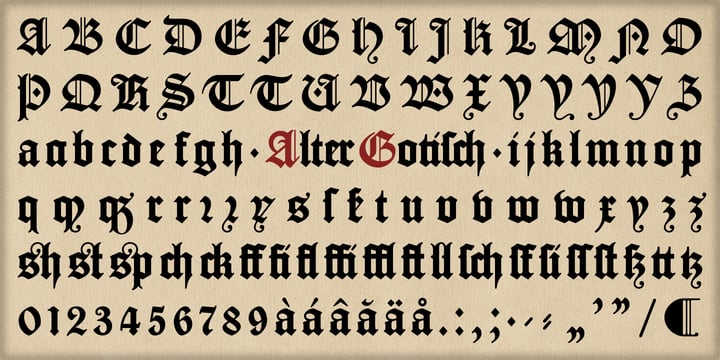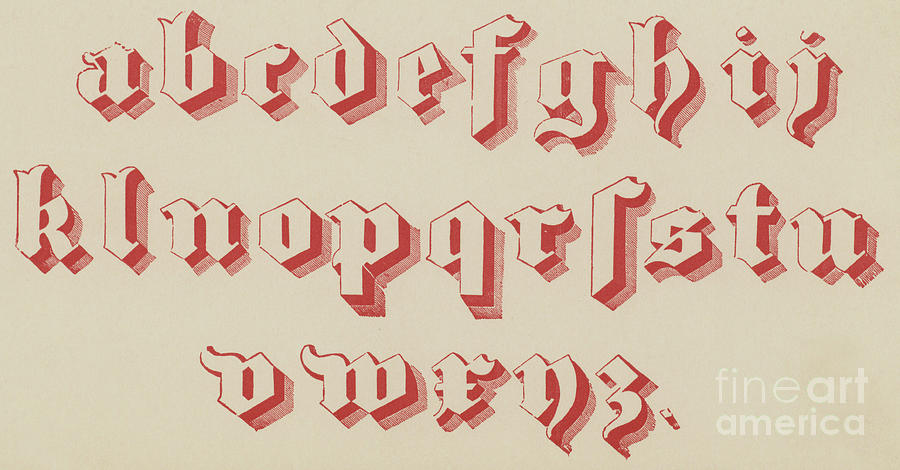
Как шрифты питают культурные войны
Типографика может представлять собой не только визуальные эффекты речи, но и серьезную опасность для общества.
Сегодня типографика словно возрождается из пепла. Обычно она старается быть невидимой, но в последнее время стала знаком изысканности для людей.
Внезапно, люди, далекие от профессии дизайнера, стали задумываться о мелочах. В том числе и о типографике продукта, с которым они взаимодействуют. В этом году премия Oscar обзавелась визуальной иерархией на карточках представления лауреатов, читатели популярного комикса XKCD никогда не упустят возможности указать на плохой кернинг, а в интернете кто-то постоянно шутит над шрифтом Comic Sans.
Но, сосредотачиваясь на мелких недостатках, мы упускаем общий смысл. Типографика не просто служит улучшению читабельности визуальных эффектов. Типографике свойственно скрытое влияние: она может обозначить опасные идеи, облагородить тиранию и разорвать связи между братскими народами. В некоторых случаях типографика даже призывает выбирать между жизнью и смертью. Она может сделать это так же мощно, как и слова, которые отображает.
Почему на Западе боятся использовать готический шрифт
Все видели готический шрифт в типографике. Он плотный, старомодный и замысловатый. Почти всегда воспринимается как анахронизм. Примерно как тут:
Но в популярной культуре все обычно представляют его вот так:
Или так:
Татуировка, обозначающая принадлежность к группировке MS-13
Старопечатный шрифт воспринимается как неотъемлемая часть имиджа плохих парней, тюремных татуировок, дизайна блэк-метал рок групп. На самом деле все так и есть.
Готика выглядит сейчас как нечто таинственное и неразборчивое, но все начиналось с обычного шаблона, который люди во всей Европе использовали в течение сотен лет.
Он был доминирующим шрифтом в англоязычном мире в течение нескольких поколений, и даже сегодня остается весьма популярным среди испано-говорящей части мира.
Типичный пример старопечатания
Почему бы нам не использовать больше старопечатных шрифтов? Ответ прост — потому что Гитлер. Руководство Германии использовало фрактуру как официальный стиль своей типографики. Они позиционировали его как символ немецкого национального самосознания и осуждали документы, напечатанные другим шрифтом.
Поэтому в послевоенный период Готика не выдержала конкуренции из-за своего бэкграунда. За несколько лет старопечатный стиль перешел из обычного и широко распространенного в табу, ровно как и другие символы нацизма вроде имени «Адольф» и усы — зубная щетка.
Сами нацисты тоже сыграли свою роль в этом. В 1941 году режим Третьего рейха переквалифицировал фрактуру, как Judenletter (еврейское письмо) и систематически запретило его использование. Продолжительная история еврейской письменности и книгопечатания «испортила» буквы, поэтому режим Гитлера утверждал, что запрет необходим для того, чтобы Германия могла двигаться дальше.
Историки же предполагают, что этот разворот нацистских властей был связан с логистикой оккупационных латинских стран, но результат был тот же: никакой фрактуры в печатном производстве — ни для немецкой аудитории, ни за рубежом. Даже старопечатный почерк был запрещен в школах.
Подумайте о том, что правительство одной из некогда великих держав мира запретили шрифт. Это и есть власть символа.
Трудности набора текста на арабском
Нам всем кажется само собой разумеющимся то, что мы можем ввести любое слово с клавиатуры, но на самом деле это исключительная привилегия латинских и кириллических письменностей. На английском языке каждая буква строго очерчена, в то время как в арабском языке буквы объединяются в словах, чтобы принимать новые формы в зависимости от контекста. Арабская письменность поддается пышной и поэтической каллиграфии, что сильно отличает её от традиционного европейского метода создания шрифтов.
Арабская каллиграфия стирает границы между письменностью и искусством
Большая часть арабского мира, попавшая под западное колониальное господство, испытывает сегодня проблемы в печатном производстве.
Они пытаются переосмыслить и расширить возможности арабской вязи за счет латинского алфавита, который колониальные державы привнесли в арабский язык. То, что можно увидеть в арабских газетах сейчас является призраком арабской вязи, которая была переделана с учетом дискретности букв для удобства набора печатного текста.
Популярный шрифт для арабского языка — Yakout, разработанный немецкими и британскими компаниями Linotype и Machinery Ltd
Неудивительно, что колониальные державы пытались нивелировать стилистические различия в языках своих колоний. Но даже сегодня многие арабские страны пытаются бороться со своим наследием. Существует более ста тысяч способов форматизации букв на английском языке, в то время как арабский язык поддерживается всего сотней неуклюжих шрифтов, служащих для полутора миллиарда человек.
Рана Абу Рейли — современный ливанский дизайнер, которая занимается возрождением арабской типографики. После учебы в США и Великобритании, она разработала Mirsaal — экспериментальный шрифт для преодоления разрыва между арабским и латинским текстом.
современный модернизм не мог ускользнуть от Реннера (которого в 1933 году в кратчайшие сроки уволили с его профессионального поста) или его Futura.